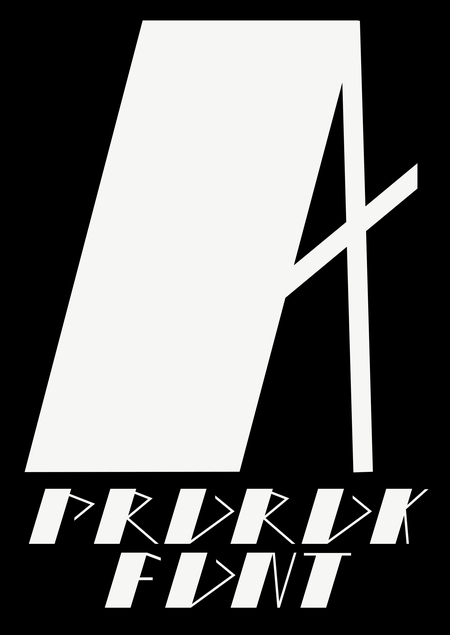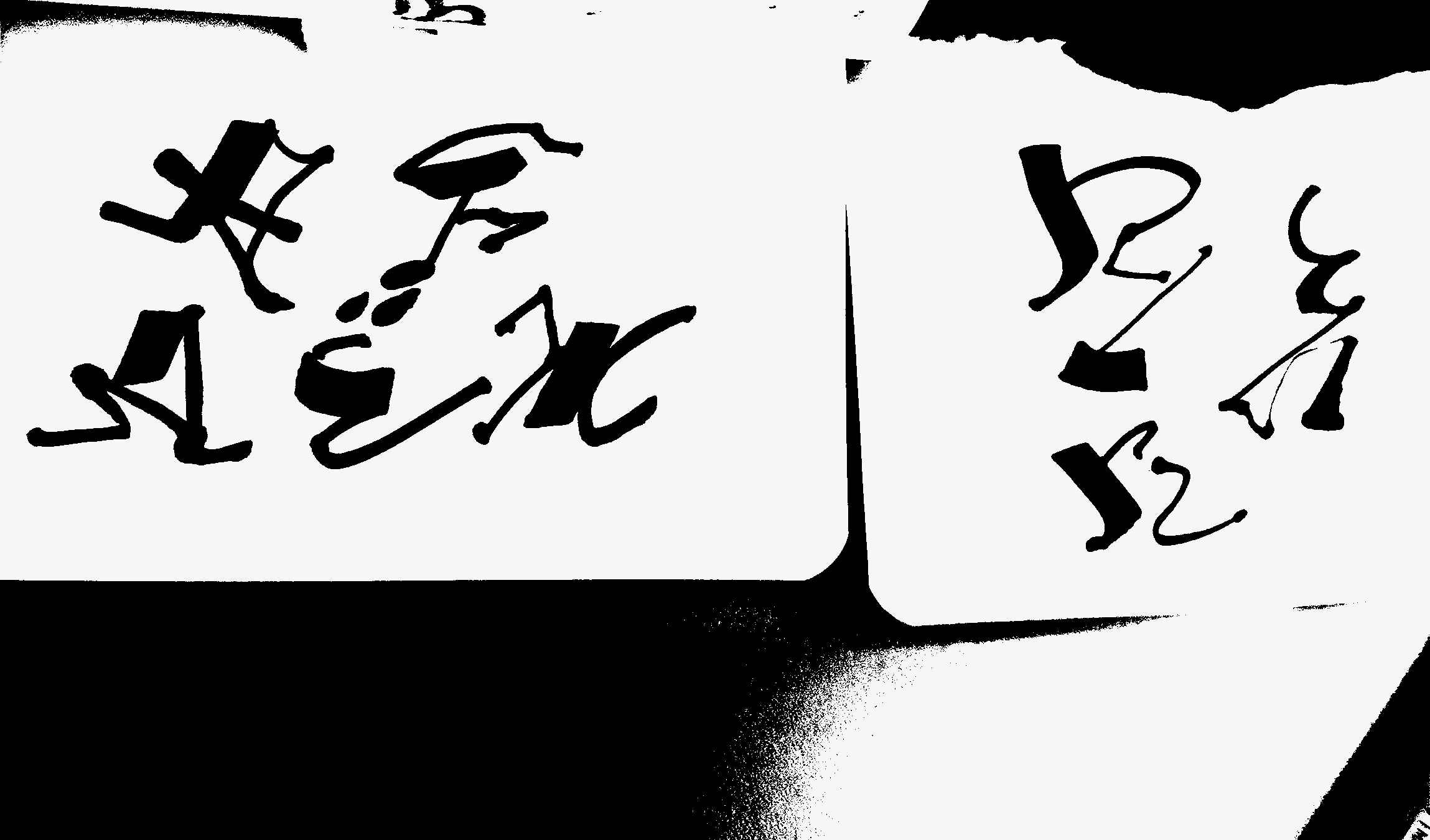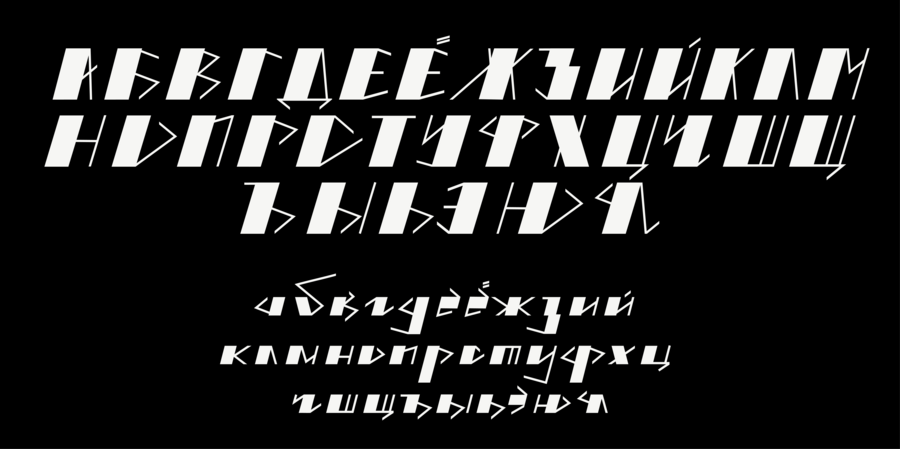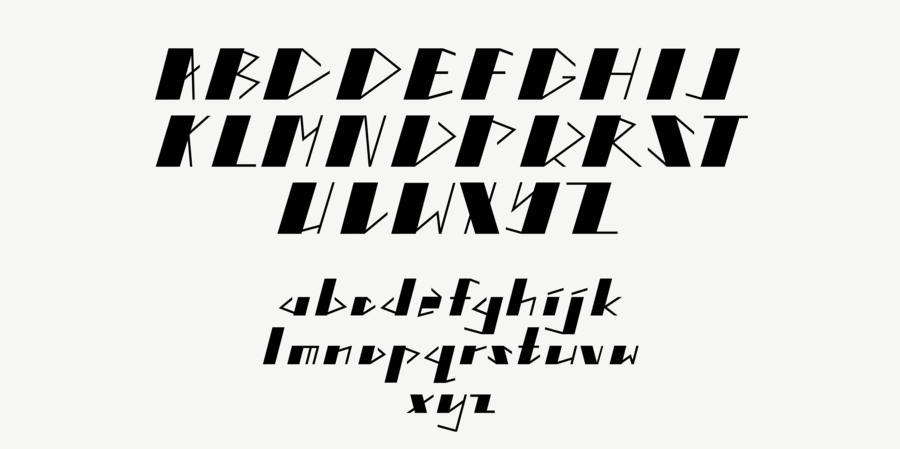
PROROK FONT
PROROK — шрифт, вдохновлённый неповторимым стилем Михаила Врубеля, в котором выразительные образы формируются из пятен-осколков и широких мазков в кристаллической технике. Каждая буква основана на крупном «мазке», создающем контраст с тонкими линиями
[1] Массивный стем с наклоном, [2] Тонкие диагонали, [3] Перпендикулярный срез концевых элементов, [4] Заострённые углы, [5] Асимметрия
«Грани» — выставка Михаила Врубеля
Выставка приглашает погрузиться в мир художника-мифотворца, чье творчество граничит между реальностью и фантазией. Экспозиция — путешествие по мифологическим сюжетам и творческим поискам символиста